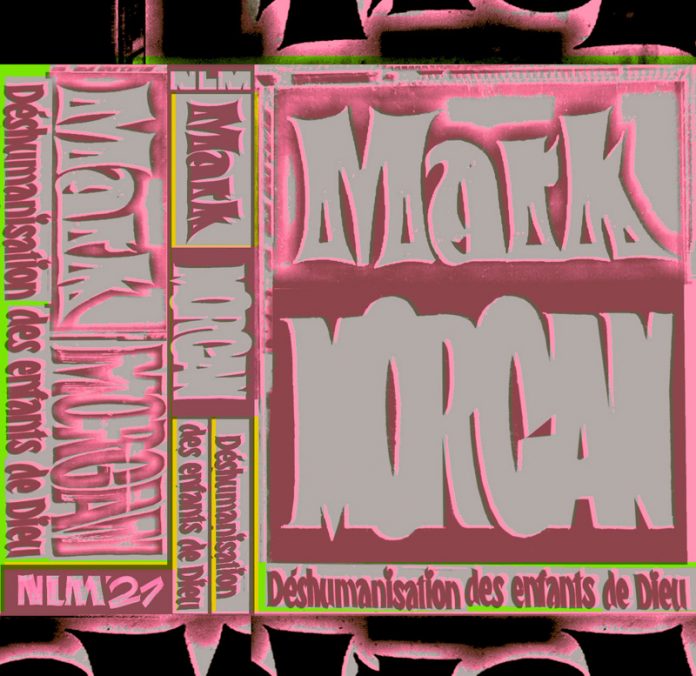
L’art de réinventer la typographie contemporaine
Typographie en mouvement : Hélène Marian, l’audace au bout des lettres
Déjà mise à l’honneur dans le numéro 271 d’étapes :, Hélène Marian continue de marquer le paysage typographique par son approche audacieuse et expérimentale. En 2025, alors que la typographie est plus que jamais un terrain d’innovation, son travail résonne avec les nouvelles attentes du design graphique : explorer les frontières entre technique et art, et donner aux lettres une voix singulière.
Hélène Marian incarne une nouvelle génération de typographes, audacieuses et polyvalentes, qui repensent sans cesse leur pratique. Son approche de la typographie se distingue par une recherche constante, explorant les limites des outils, des supports et du geste créatif. Cette démarche expérimentale donne naissance à des projets innovants qui réinterprètent les codes classiques du design de caractères.
Un parcours atypique, entre dessin et typographie
Avant de devenir une figure reconnue dans le milieu, Hélène Marian s’est d’abord formée à l’illustration. Cette première étape de son parcours a influencé sa vision de la typographie : ses projets graphiques intégraient de plus en plus de textes, jusqu’à ce que les lettres surpassent le dessin. Cette transition naturelle l’a menée vers des formations spécialisées en typographie, lui permettant de poser les bases techniques nécessaires pour son travail.
Cependant, Marian ne s’est jamais contentée des méthodes traditionnelles : elle a cherché à s’émanciper des cadres établis. Sa rencontre avec la peinture en lettres, apprise de manière autodidacte, a marqué un tournant dans sa pratique. Ce médium lui a offert une liberté d’expression inédite, propice à l’improvisation et aux formes imprévues.
Entre expérimentation et collaborations
Son exploration de la peinture en lettres l’a amenée à collaborer avec des labels de musique expérimentale, où l’absence de règles strictes faisait écho à sa propre quête artistique. Ces expériences ont enrichi sa manière d’aborder le design typographique : textures, dérapages contrôlés et hasard sont devenus des éléments constitutifs de son univers créatif.
Par ailleurs, son partenariat avec des studios et des fonderies typographiques a élargi son champ d’action. Elle a notamment conçu des familles typographiques qui interrogent les contraintes du format et des outils, ouvrant la voie à des créations radicales et sans cesse renouvelées.
Typographie et design éditorial
Hélène Marian navigue avec aisance entre plusieurs disciplines, de la création typographique à la mise en page éditoriale. Cette transversalité lui permet d’aborder chaque projet avec une vision globale, où les lettres ne sont pas simplement des éléments fonctionnels, mais des acteurs à part entière du discours visuel.
L’un de ses projets récents illustre parfaitement cette synergie : la création de typographies sur mesure pour un ouvrage bilingue, où elle a su résoudre des contraintes linguistiques tout en ajoutant une dimension narrative inspirée de l’environnement urbain. Ce travail souligne sa capacité à allier rigueur technique et créativité, sans jamais perdre de vue l’essence du projet.
Une pratique en perpétuelle évolution
Pour Hélène Marian, les outils ne sont jamais une fin en soi. Au contraire, elle préfère questionner leur usage et expérimenter des méthodes alternatives, parfois inconfortables, mais toujours stimulantes. Cette remise en question permanente de ses moyens de production lui permet d’explorer des territoires inédits et de maintenir une dynamique créative.
À travers son travail, Marian redéfinit les contours de la typographie contemporaine. En repoussant les limites de la discipline, elle prouve que la lettre, bien plus qu’un simple support de lecture, est un terrain d’expression infini où l’innovation rencontre l’artisanat.